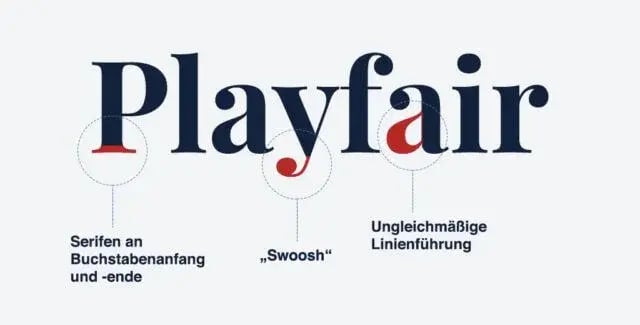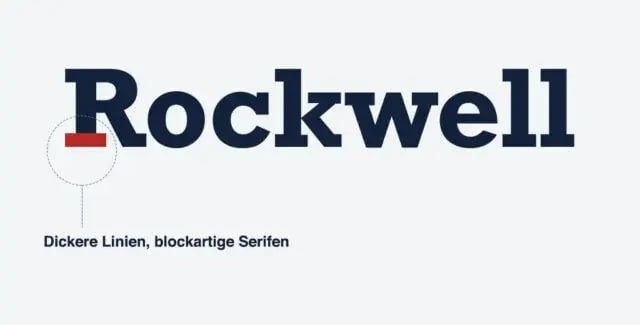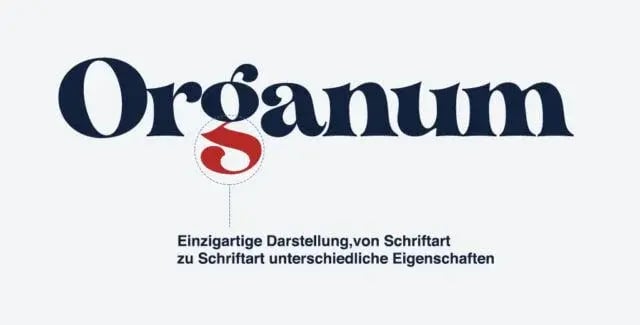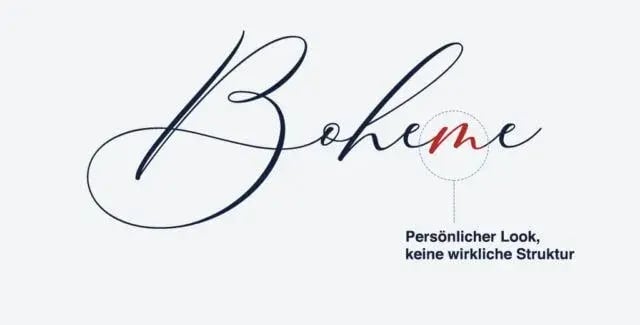
Immer wieder werden wir gefragt: Welche Schriftarten gibt es? Hinter dieser Frage verbirgt sich meist der Wunsch, überhaupt erstmal eine Grundorientierung im Dschungel der Typografie zu schaffen. Denn Schriftarten gibt es wie Sand am Meer. Oder wie Buchstaben in der Buchstabensuppe. Allein Google stellt unter Google Fonts ungefähr 1000 Schriftarten kostenlos zur Verfügung.
In diesem Artikel geben wir dir eine Übersicht über die verschiedenen Typen an Schriftarten. Außerdem erfährst du, für welchen Zweck welche Schriftart besonders gut geeignet ist. Übrigens: Dieser Artikel verwendet die Schriftart „Lato“, eine serifenlose Schrift. Was das heißt?
Lies weiter, dann erfährst du es! Und vielleicht hast du angesichts unserer Übersicht ja auch eine Idee, warum wir uns ausgerechnet für diese Schriftart entschieden haben…
Darum ist es so wichtig, welche Schriftart du auswählst
Modernes Unternehmen, altbackene Schriftart – das passt nicht zusammen.
Das Logo der Konditorei in Schreibschrift? – Passt schon eher!
Ob für die Website, einen Flyer oder das Unternehmenslogo – mit der Wahl einer passenden Schriftart wertest du dein Unternehmen und deine Produkte enorm auf und begeisterst deine Leser, Interessenten und Kunden. Denn wenn die von dir gewählte Schriftart und dein Markenkern harmonieren, wirkt dein gesamter Unternehmensauftritt insgesamt viel stimmiger.
Gleichzeitig haben klug ausgewählte Schriftarten ganz praktische Funktionen: Texte sind besonders leserlich oder wecken die Aufmerksamkeit der Leser. Für Broschüren-Texte, Onlineformate und Werbebanner gilt es den Fokus hier ganz verschieden zu setzen. Denn die meisten Schriftarten sind nicht gut oder schlecht (abgesehen von Comic Sans, die ist wirklich schlecht), sondern passen oder passen nicht für ganz konkrete Zwecke. Lies weiter, um zu erfahren, welche Schriftarten es gibt und für wen und wofür sie sich besonders eignen.
Schriftart-Typen
1. Serifenlose Schriften
Serifenlose Schriften verzichten auf Serifen (Linien als Abschluss von Buchstaben). Sie sind schlicht, schnörkellos und wirken daher gegenüber den klassischen Serifenschriften eher modern. Dabei zeichnen sie sich durch eine klare Linienführung aus. Einige serifenlose Schriften tragen das „Sans“ (von frz. sans – dt. „ohne“) oder „Sans Serif“ (dt. „ohne Serif“) im Namen, so zum Beispiel Merriweather Sans.
Geeignet für:
Aufgrund der schlichten Gestalt eignen sich serifenlose Schriften für die Vermittlung von Sachinformationen sowie für Unternehmen, die einen unkomplizierten Eindruck erwecken möchten. Das beste Beispiel dafür ist Google, das sein Logo im Jahr 2015 von einer Serifenschriftart zu einer serifenlosen Schrift geändert hat. Warum? Damit auch im simplen Logo die einfache Nutzung der Suchmaschine versinnbildlicht wird. Die Google-Startseite umfasst lediglich das Logo und eine Suchmaske – das sind Schlichtheit und Einfachheit pur, die als Markenkern mit diesem Logo zusätzlich betont werden.
Aufgrund ihrer Schlichtheit eignen sie sich nicht nur für informative Texte wie Verkehrsschilder, Sachbücher und offizielle Dokumente, sondern auch für Texte auf Websites und in Apps – besonders deshalb, weil sie auf allen Bildschirmtypen und -größen gut lesbar abgebildet werden. Im Gegensatz zum Zeitungs- und Buchlesen werden digitale Texte weniger nach Linien, sondern verstärkt nach Absätzen untergliedert, weshalb die unterstützende Linienführung der Serifenschriften hier nicht so stark ins Gewicht fällt.
Auf den ersten Blick wirken serifenlose Schriften zwar unscheinbar. Gerade dickere Buchstaben – etwa in fettem Druck – können aber durchaus die Aufmerksamkeit des Lesers auf sich ziehen, weshalb dieser Schrifttyp auch von einigen Firmenlogos genutzt wird.
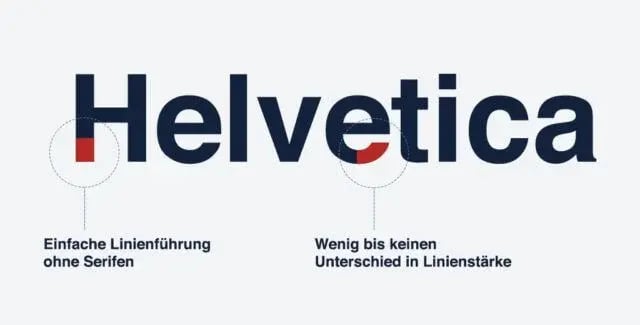
Entstehung:
Die erste serifenlose Schriftart wurde im Jahr 1816 in England gegossen. Ihr Erfinder William Caslon nannte sie übrigens „English Egyptian“ – in dieser Namensgebung spiegelt sich die Ägyptenmode, die auch für die Schriftarten vom Typ der „Egyptienne“ prägend werden sollte. Besondere Verbreitung fanden serifenlose Schriften vor allem in den 1920er und 1930er Jahren. Serifenlose Schriften wurden aufgrund ihres einst ungewohnten Erscheinungsbildes früher als auch „Grotesk“ bezeichnet – ein Name, der sich bis heute in einigen Bezeichnungen erhalten hat. Die bekannte serifenlose Schriftart Helvetica zum Beispiel, die in den 1950er Jahren in Deutschland erfunden wurde, trug zu Anfang auch den Namen „Neue Haas Grotesk“. Eine noch weitere Verbreitung fand die Schriftart Arial, die 1982 entwickelt wurde, um auf Bildschirmen besonders lesbar zu sein – nicht immer waren Bildschirme so hochauflösend wie heute.
Marken mit serifenlosen Schriften:
Vorteile:
Schriften ohne Serifen sind auf das Wesentliche reduziert. Sie wirken sauber, präzise und bringen damit neben Klarheit, Schlichtheit und Einfachheit auch Effizienz zum Ausdruck. Durch den Verzicht auf die klassischen Verzierungselemente wirken sie im Vergleich zu Serifenschriften meist moderner. Zudem behalten sie ihre Lesbarkeit auch bei kleinen Schriftgrößen. Ein weiterer Vorteil ist ökonomischer Natur: bei großen Druckmengen sparst du mit serifenlosen Schriften Tinte.
Nachteile:
Im Vergleich wirken Serifenschriften weniger edel, weniger galant und bisweilen auch steril. Je nach Kontext kann das unangemessen wirken.
Beispiele für serifenlose Schriften:
2. Serifenschriften
Serifen sind meist feine Striche, die an den Rändern beziehungsweise Abschlüssen von Buchstaben – und zwar oben, unten und seitlich – hinzugefügt werden. In der Regel sind diese Serifen deutlich dünner als die Buchstaben.
Beispiele für Handschriften:
Fazit: Diese Schriftarten gibt es
Welche Schriftarten gibt es? In diesem Artikel haben wir die Hauptkategorien gezeigt, die sich in Bezug auf Schriftarten treffen lassen: serifenlose Schriften, Serifenschriften, Egyptienne, dekorative Schriftarten sowie Hand- und Schreibschriften. Natürlich lassen sich auch andere Unterscheidungskriterien einführen, zum Beispiel die Dicke, Höhe oder Breite der Buchstaben. Dennoch sollte dir unsere Übersicht weiterhelfen, grundlegende Unterschiede zwischen verschiedenen Fonts beziehungsweise Schriftarten zu erkennen, ihre jeweiligen Vorteile und Nachteile abzuwägen und die Schriftart für dein Projekt auszuwählen. Denn wenn du zunächst den geeigneten Schriftarttyp bestimmst, kannst du die Auswahl systematisch einschränken. Damit findest du die perfekte Schriftart für deine Website, dein Logo oder deinen Flyer viel schneller.